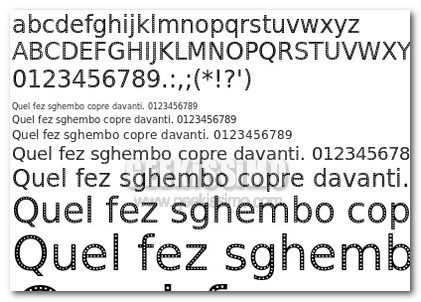
Ecologia, ecologia. Tema senz’altro importante e da non sottovalutare, tant’è che nel nostro network c’è un blog che parla proprio di questa interessantissima materia, Ecologiae.
Ma che c’entra con Geekissimo l’ecologia? Bhè, c’entra abbastanza se si considera che anche l’informatica, seppur con le dovute premesse, può andare a braccetto con l’ambiente. Come? Ve lo spieghiamo adesso!
Per chi vuole risparmiare inchiostro (e quindi vuole inquinare di meno) e soldi, oggi abbiamo una soluzione niente male. Qual è questa soluzione? Un attimo, non corriamo, ma cominciamo col dire che si chiama EcoFont!
EcoFont è un tipo di carattere, un font, che consente di risparmiare fino al 20% di inchiostro quando stamperemo un documento scritto con questo tipo di scrittura grazie ai suoi molteplici ma piccolissimi fori all’interno di lettere, numeri e simboli.
In pratica con questo font, potremo consumare decisamente meno inchiostro perché i caratteri stampati non saranno “pieni”, ma avranno dei buchetti così piccoli che, pur non disturbando la lettura di chi prenderà visione dei fogli stampati, faranno risparmiare risorse.
Un’idea, proveniente dall’Olanda, molto intelligente e rispettosa dell’ambiente. Una soluzione senz’altro poco complicata da attuare, ma che però potrà fare molto comodo ad ognuno di noi.
Geniale!
ottimo!
inoltre sulle stampanti a getto d’inchiostro non si nota la differenza da un carattere normale!
Mah sono un pò scettico su queste cose. Alla fine non si farebbe prima a stampare come bozza?
Bella idea, peccato che il risparmio di inchiostro sia FALSO!!!
Se si misura infatti la superficie nera all’interno del carattere, questa è pressoché identica a quella del Times New Roman (la differenza sarà di circa l’1%). Questo perchè pur essendo l’EcoFont bucherellato i suoi caratteri sono più spessi.
Misurare per credere 😉
Credo che il risultato sarebbe identico stampando in grigio…
Ho anche io gli stessi dubbi, poi contando che la maggior parte delle stampe in bianco e nero di testo vengono fatte a 300dpi su A4 comune non si conta lo spreco (per il solo testo risoluzioni minori sono più adatte perché non vanno ad impregnare la carta eccessivamente con l’inchiostro).
i dati che vogliono un risparmio fino al 20% provengono da studi effettuati dalla stessa casa che ha creato il font. Più di questo non saprei dirvi, non sono uno studioso di questo campo.
bella idea!
@ Trentalance:
basta solo selezionare il testo e scegliere il font, non è poi una procedura così lunga 😉
interessante la notizia del font ecologico, però bisogna imparare ad usare le pendrive e digitalizzare tutto il resto 🙂
Anche il DeMauro può sbagliare, nessuno è perfetto. Chi lavora nel mondo della grafica utilizza sempre l’articolo femminile perché sa che è quello corretto 🙂
Di certo è un dettaglio che non cambia la vita, ma è sicuramente uno di quelli che ti fa capire -con le dovute eccezioni- che l’interlocutore è professionale e sa di cosa parla.
Naturalmente prendi questa cosa come un consiglio, niente di personale contro ;P
a me sembra più facile che a sbagliare siano i grafici piuttosto che demauro…
niente di personale 😉
@MattSid
Grazie per la dritta 😉 .
Ma i grafici sono quelli che pronunciano layer o plugin così come si scrivono? Minchia, veri profescional.
@MattSid
Secondo la grammatica italiana (non l’uso “comune” come dicono su Wikipedia) ogni parola straniera usata in italiano va declinata al maschile e non ha il plurale.
Quindi IL font, I font (e non “i fonts”), il mouse, il report, il blog, ecc. ecc.
Ecco perché il DeMauro lo riporta al maschile.
Mi dispiace, ma in questo caso sono i “professionisti” che sbagliano.
Bye.
Bella notizia ma già vecchia di qualche settimana: anche sull’altro blog ovviamente si sono sprecati gli immancabili commenti disfattisti del tipo “ah ma si risparmia poco inchiostro”, “ah ma si può usare la modalità bozza”, ecc.
Io dico che ogni innovazione che porti ad un risparmio di risorse, fosse anche dello 0,0001% debba essere sempre accolta con entusiasmo, quindi i miei applausi a un team che ha saputo dare risposta ad uno dei problemi più pressanti della società contemporanea.
Spero di aver scritto tutto in modo corretto, non vorrei finire nelle grinfie di qualche correttore professionale… 😉
Effettivamente è molto più spesso degli altri font, EcoFont a 9pt è pressoché identico a Times New Roman 12pt.
Basta ricordarsi di diminuirne la dimensione…
Lo avevo scaricato da quando lo hanno segnalato su mambro e mi sembrava una bella idea. Ieri l’ho provato ed è proprio vero che si notano pochissimo i buchi.
Per quanto riguarda il risparmio effettivo non saprei, ma posso dire di concordare con OXO e di apprezzare quest’innovazione quantunque si risparmi meno del 20% con caratteri piccoli.
Per la cronaca sul sito non sostengono che si possa risparmiare sempre e comunque il 20%… (vedasi http://www.ecofont.eu/results.html )